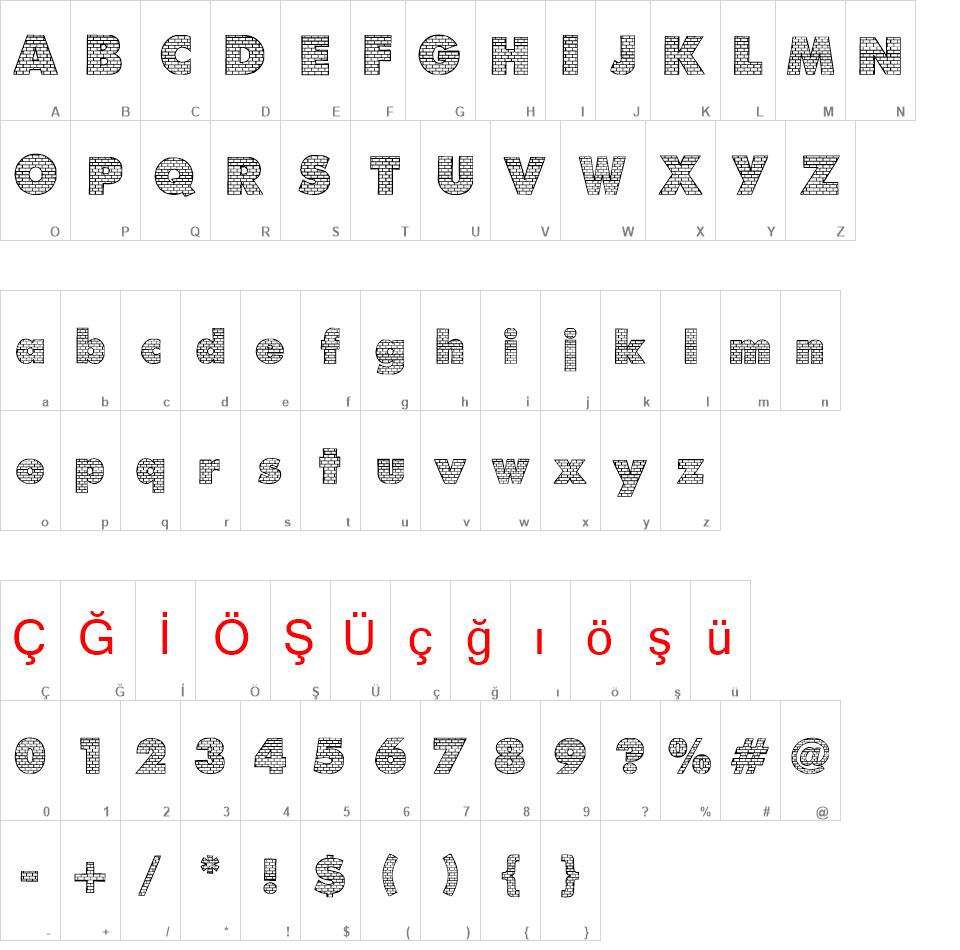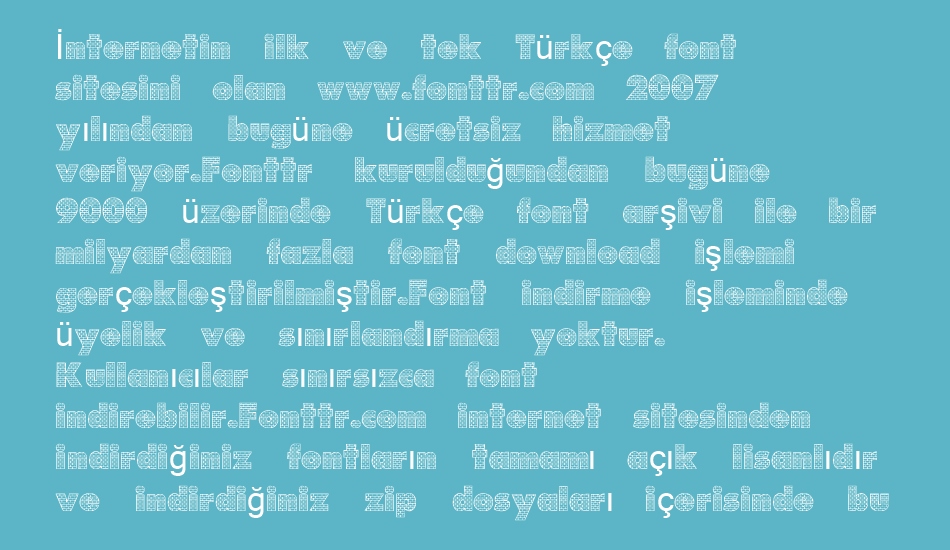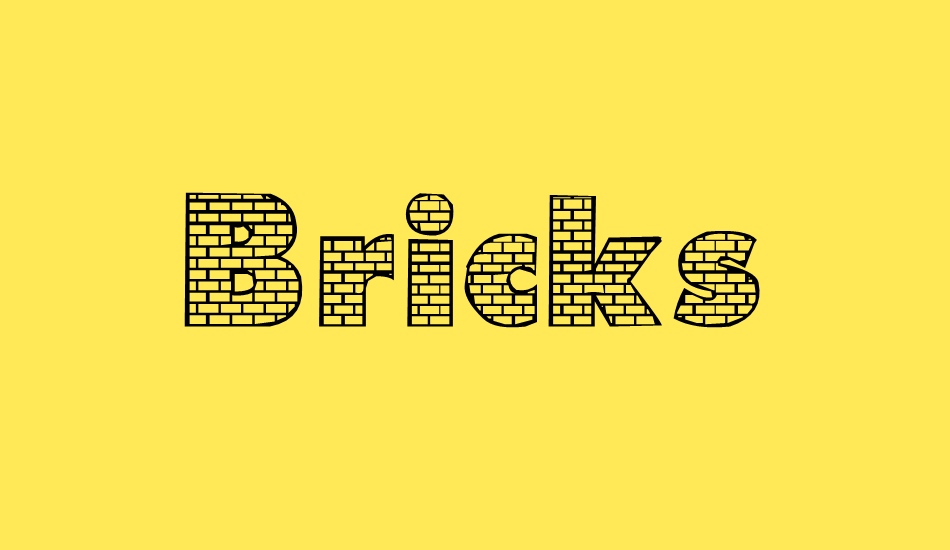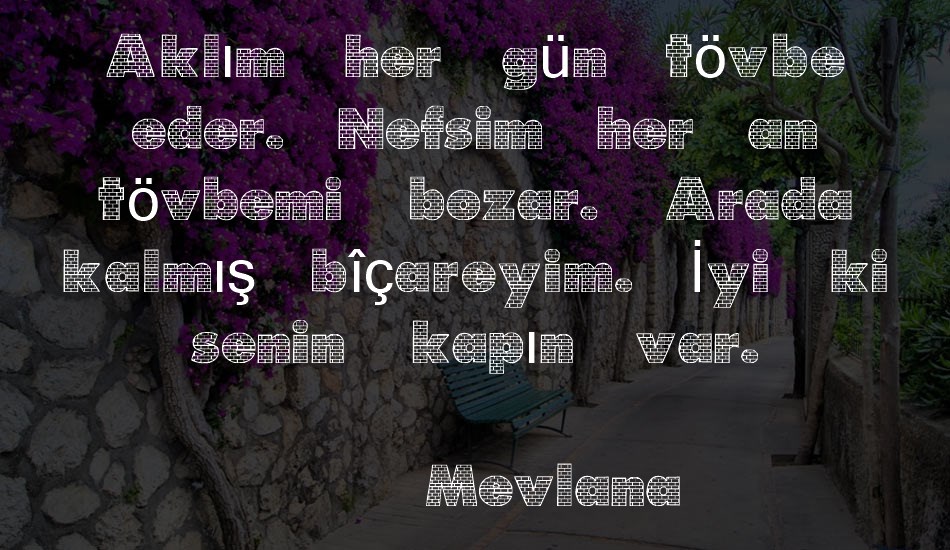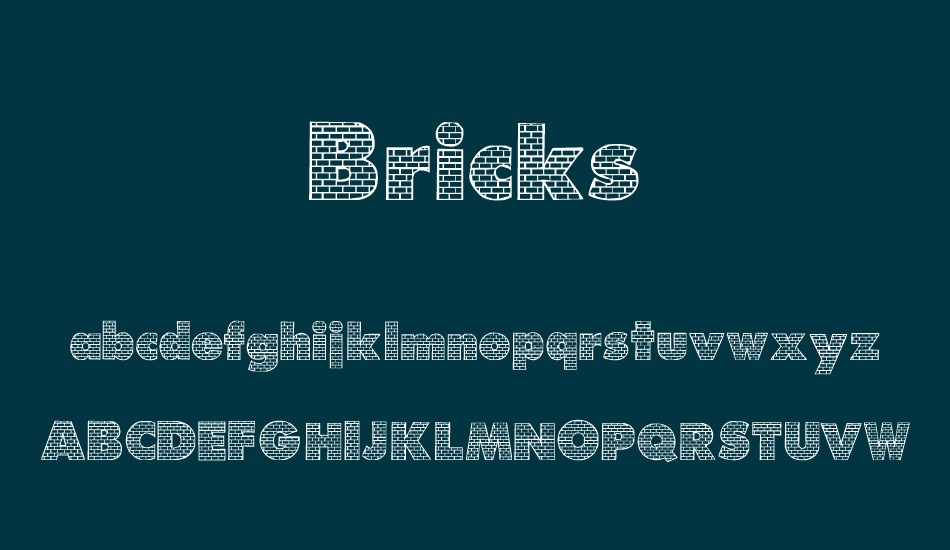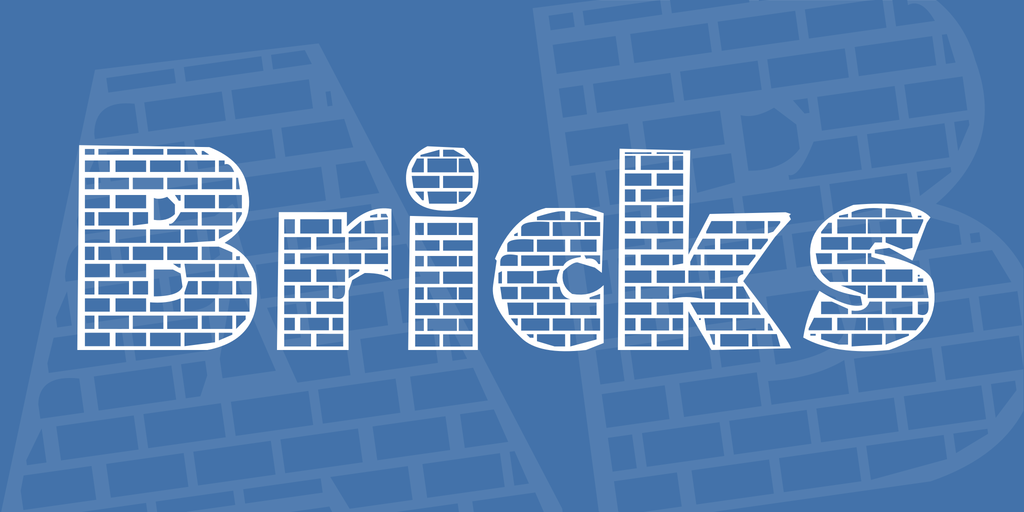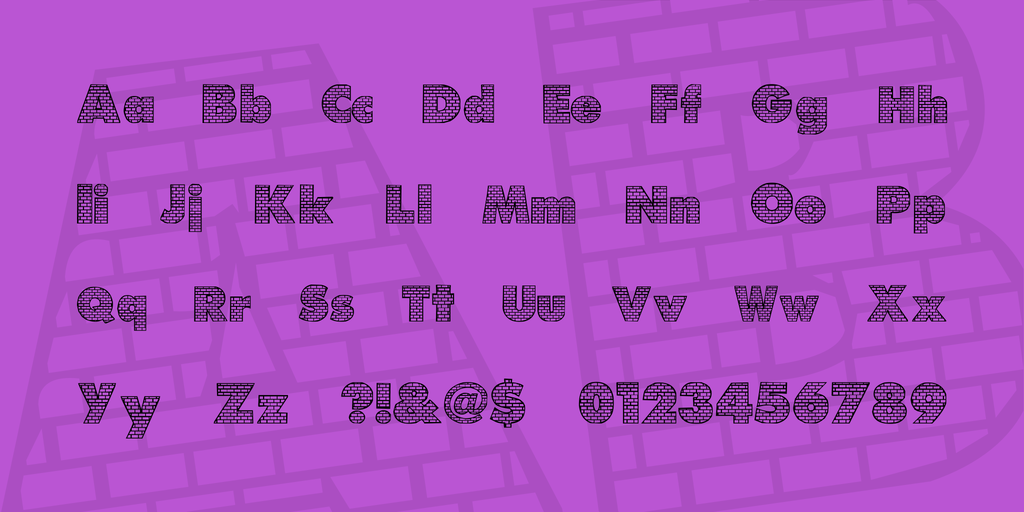
BRICK font
BRICK
Eine True Type dekorative ANSI-Schriftart. Es wird empfohlen, diese Schriftart erst ab 24pt zu verwenden, da das Ziegelmuster in kleineren Größen verzerrt wird.